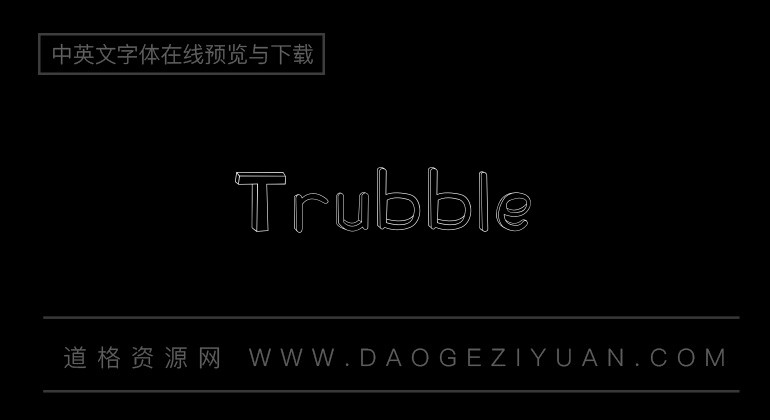
Trubble 是一款由 Monotype 公司推出的投影字体,它专为屏幕显示而设计,以提升阅读体验。Trubble 字体具有凸起的笔画,可以更清晰地将字母和字符分离,从而提高在屏幕上的可读性。它的字体设计也更加简洁,可以更好地展示文本内容。此外,Trubble 字体还具有更大的行距,使字体更加清晰,更容易阅读。内容介绍
Trubble是一款非常不错的手写艺术字体,具有很好的视觉感,适合于文化类的宣传设计、商业类品牌的广告和产品包装设计以及个性化文字排版等较多场景。